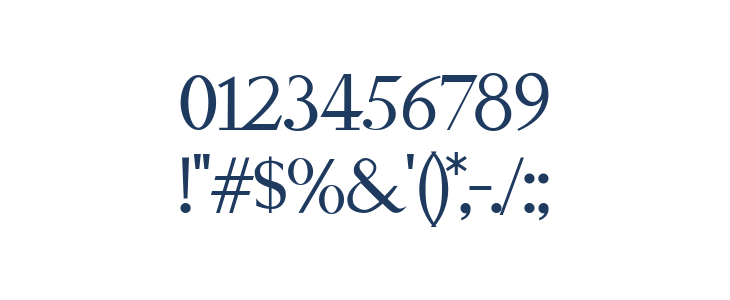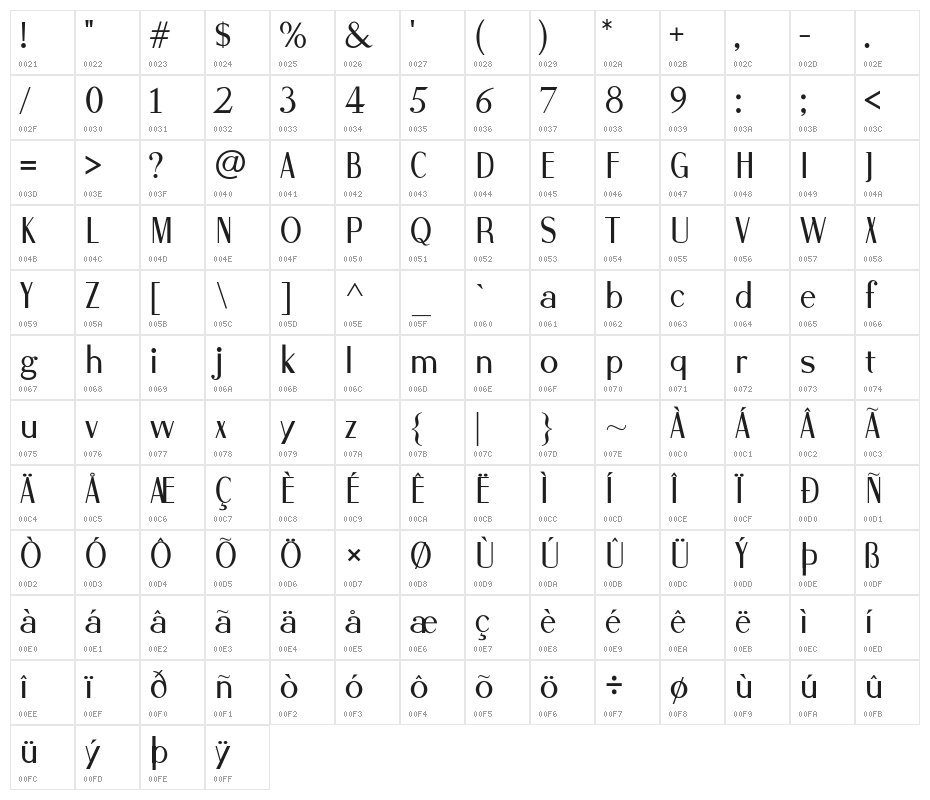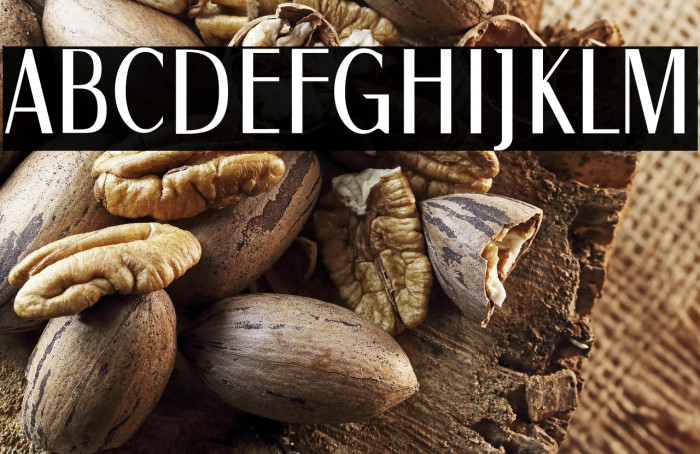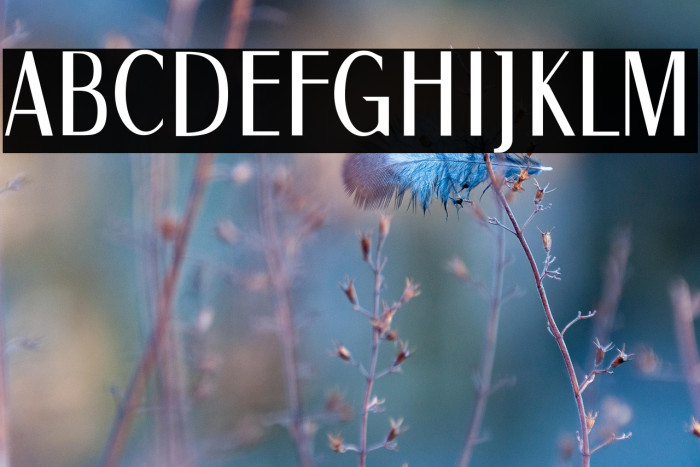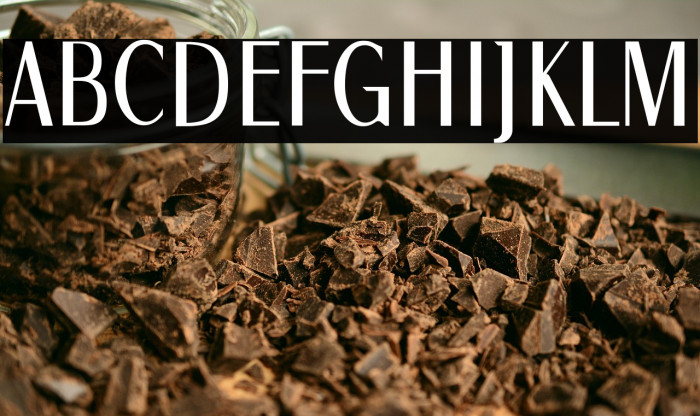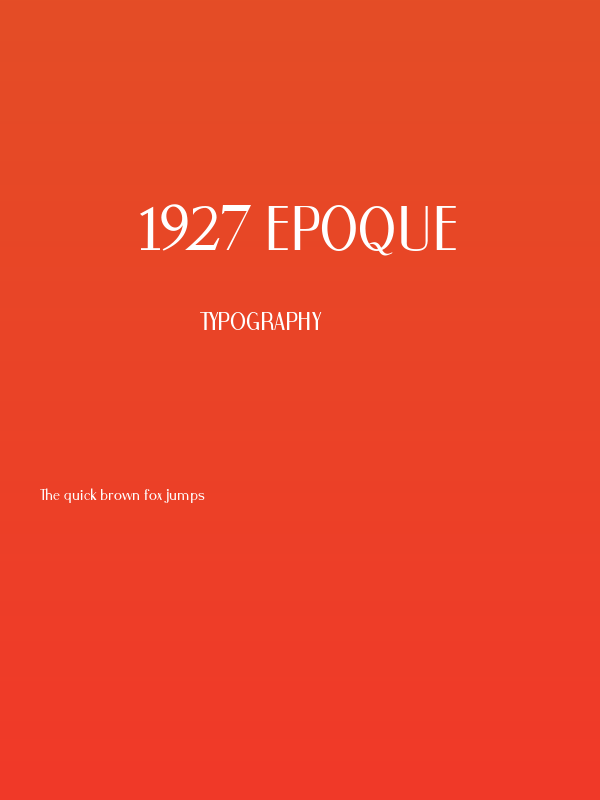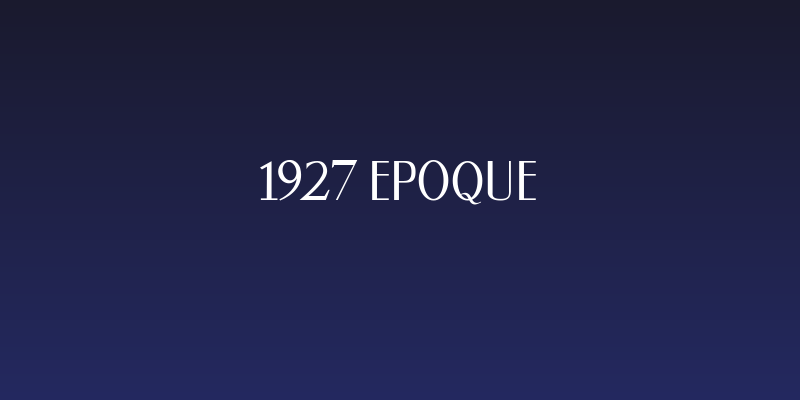
1927 Epoque Font
✎ Thick
| Kategorien | Thick |
| Gesamtstil | Classic |
| Anwendungsfall | Headlines, Logos, Editorial design |
| Vorgeschlagene Projekte | Ideal for luxury branding, editorial design, wedding invitations, and high-end product packaging. |